Шрифты русские для логотипов – 20 шрифтов для логотипов и заголовков
20 шрифтов для логотипов и заголовков
Мы собрали 20 современных шрифтов для логотипов и заголовков, это по-настоящему хипстерская подборка. Погнали!
Для логотипов подходят разные шрифты, не только акцидентные. Какой выбрать шрифт? Зависит от ваших задач! В нашей сегодняшней небольшой коллекции в основном модные нынче винтажные шрифты, и в тоже время имеются футуристичные, геометричные. В скором времени, будут еще сочные подборки, не пропусти в разделе графики для сайта.
Portico
Exodus
Выглядит мистично, не правда ли?
Soda Fountain
Highliner
Amsterdam Superstar
Геометричный шрифт.
Rubik
Accuratist
Новый шрифт от студента курса «Интенсивная типографика» в Москве.
Bernier
Arciform
Balqis
Measure
Nazare
Shirota
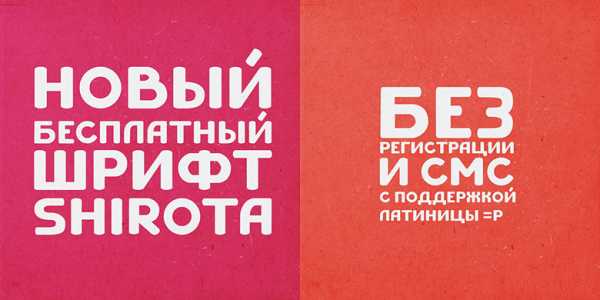
Dewberry
Gagalin
Blackentina 4F
Lumberjack
Marsh Stencil
Отличный трафаретный шрифт.
Eleventh Square
Автор — Евгений Тарасенко. Новый шрифт от студента курса «Интенсивная типографика» в Москве.
Bukhari Script
30 красивых шрифтов для вашего логотипа
Когда вы работаете над созданием фирменного стиля бренда (в частности, логотипа), шрифт является одним из ваших главных союзников. Поэтому к выбору оптимального шрифта следует подходить максимально ответственно. Он должен быть одновременно красивым, разборчивым и оригинальным, иметь ярко выраженный характер и уместно смотреться в разных контекстах.
При выборе шрифта необходимо учитывать историю и особенности вашей компании, а также сферы применения будущего логотипа. Также следует помнить о том, что дизайн вашей эмблемы должен оставаться актуальным на протяжении не одного года. Интерестные идеи для логотипов вы можете найти здесь.
1. CLOUD SANS
Шрифт класса гуманист без засечек, слегка напоминающий гротеск. Универсален в использовании. Имеет 5 степеней насыщенности. Светлый и жирный варианты доступны бесплатно!
2. QANELAS SOFT
Qanelas Soft — современный, красивый, без засечек и с уклоном в геометрию. Это более мягкая, «дружелюбная» версия семейства Qanelas.
3. BRAVO
Красивый руский шрифт с множеством глифов и символов.
4. TROCCHI
Прямоугольные засечки придают Trocchi непринужденный, легкий вид. Trocchi прекрасно подойдет как для текстов, так и для графических объектов. Он получил свое название в честь шотландского писателя Александра Трокки.
5. BEBAS NEUE
Bebas Neue это семейство без засечек, созданное на основе оригинального бесплатного шрифта Bebas Neue авторства Руичи Тсунекава (Ryoichi Tsunekawa). Он приобрел огромную популярность, получив прозвище «новый Helvetica среди бесплатных шрифтов». Благодаря команде дизайнеров из Fontfabric семейство пополнилось четырьмя новыми видами – тонкий, светлый, книжный и нормальный. Они с новыми степенями насыщенности остаются верными стилю Bebas: это такие же простые линии, элегантные формы и комбинация технической прямоты с понятной каждому теплотой. Идеальный варианты для экрана и печати, коммерческого и художественного использования.
6. VAST SHADOW
Vast — викторианский рекламный с прямолинейными засечками. Создает ощущение надежности и цельности, с легким оттенком элегантности.
7. NORWESTER
Сжатый геометрический шрифт без засечек с заглавными буквами, малыми заглавными буквами, цифрами и разнообразными символами. Разработан Джейми Уилсоном (Jamie Wilson).